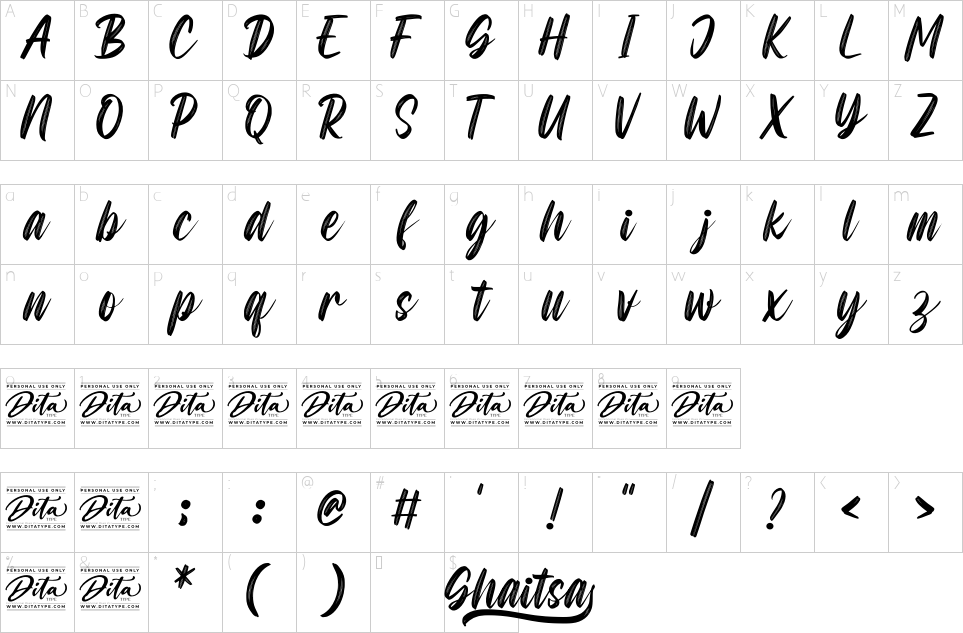
A fonte Ghaitsa é uma opção ideal para designers que buscam adicionar um toque distintivo a seus projetos digitais. Desenhada pelo Dita type, esta font foi especialmente criada para se encaixar em qualquer layout gráfico. Com um design arrojado e moderno, Ghaitsa oferece uma variedade de opções de estilo que vão do claro e elegante ao mais atraente e vibrante, dependendo da sua necessidade específica. Com suas 6.321 downloads, a Ghaitsa é frequentemente escolhida por designers em busca de um recurso semelhante mas com uma paleta mais rica e versátil que pode complementar outros estilos existentes. É perfeitamente compatível tanto para uso no Windows quanto no Mac, tornando-a uma fonte fácil de acessar e usável nas maiores plataformas de design digital. Essa fonte é uma ótima escolha para projetos web, interfaces gráficas ou qualquer outro projeto que se beneficia do estilo único da Ghaitsa. Com sua versatilidade, você pode encontrar um tom perfeito para seu trabalho e garantir um visual atraente e diferenciado em cada projeto.